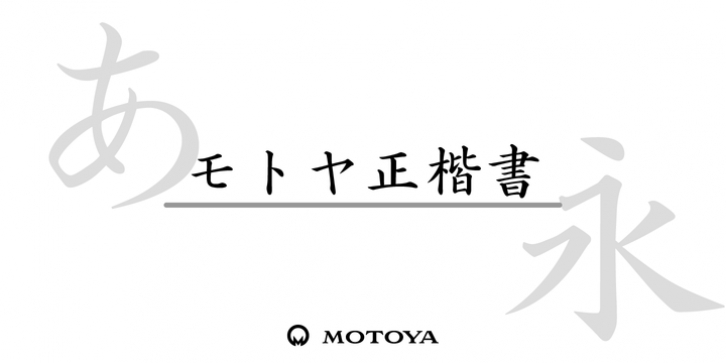
Motoya Seikai was published by Motoya. Motoya Seikai contains 2 styles and family package options.
æ£æ¥·æ›¸3ã®æ¬§æ–‡ãƒ»æ•°å—ã®å¤©åœ°ã‚’å°‘ã—å°ã•ãã—ã€å¾“æ¥ã®Centuryç³»ã‹ã‚‰å„ªé›…ãªæ£æ¥·æ›¸ã®å°è±¡ã«ã‚ã£ãŸç†æ–‡å—ã®ãƒ‡ã‚¶ã‚¤ãƒ³ã«ã—ã¾ã—ãŸã€‚
Motoya Seikai Std W3·